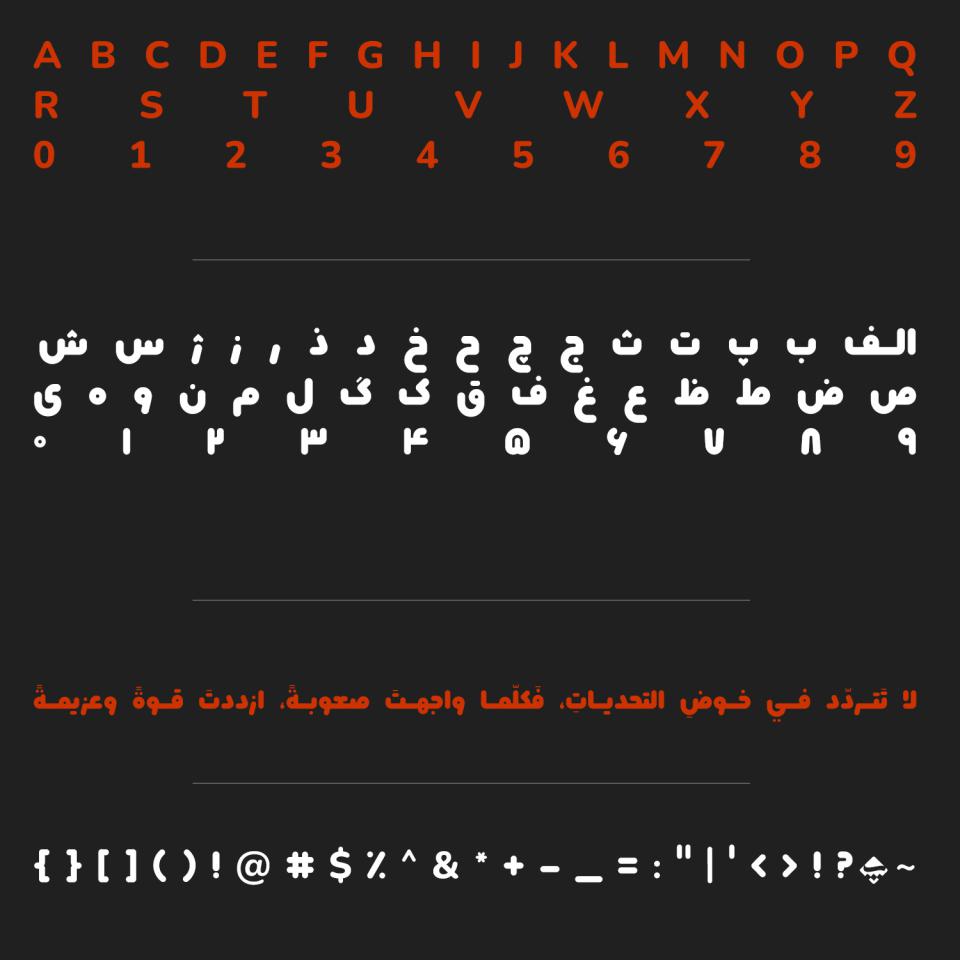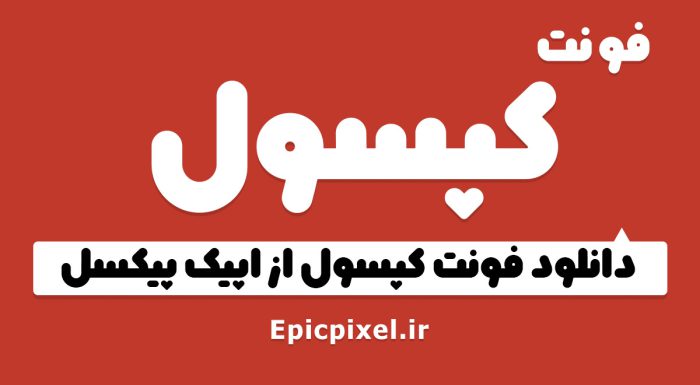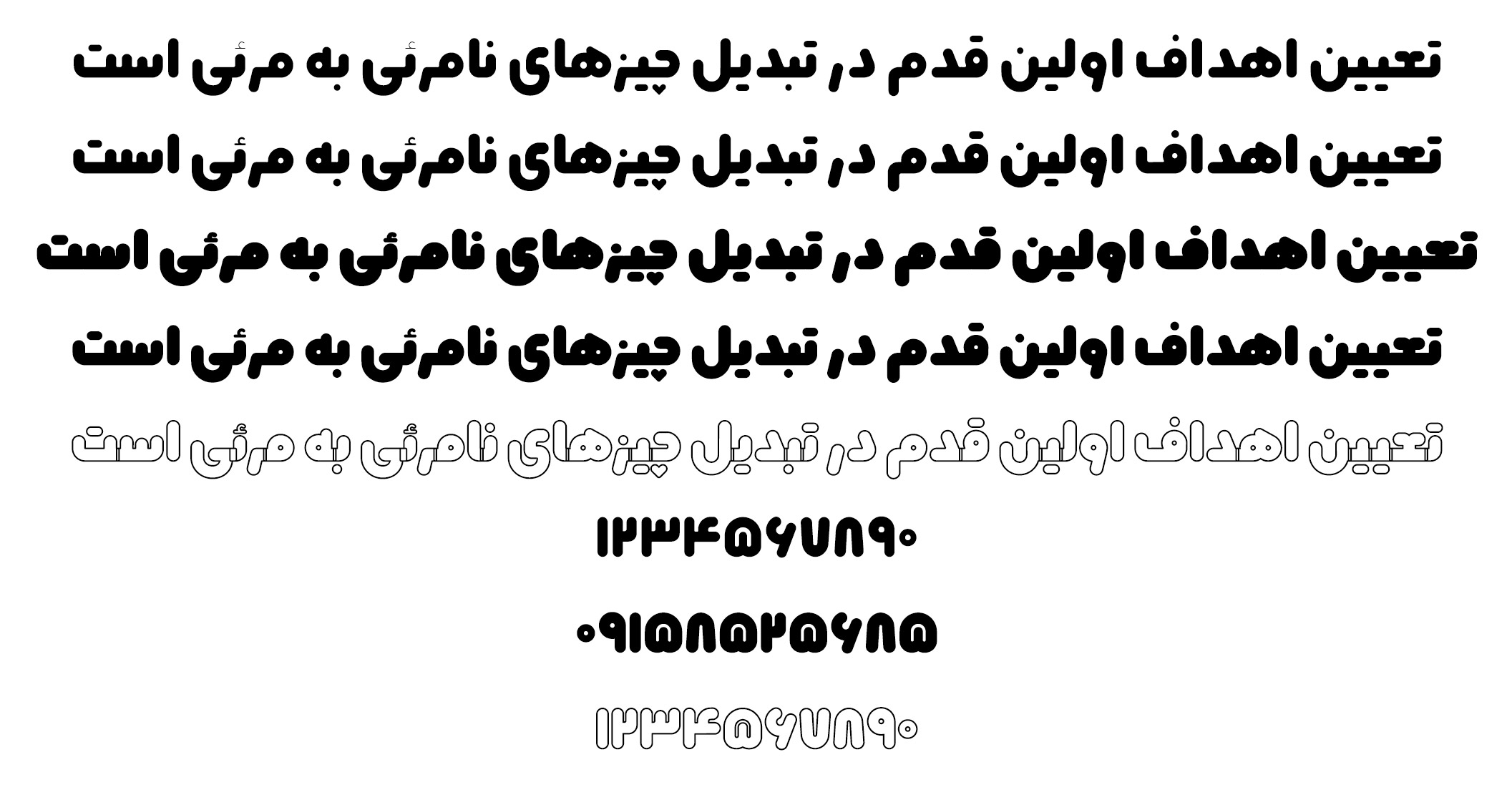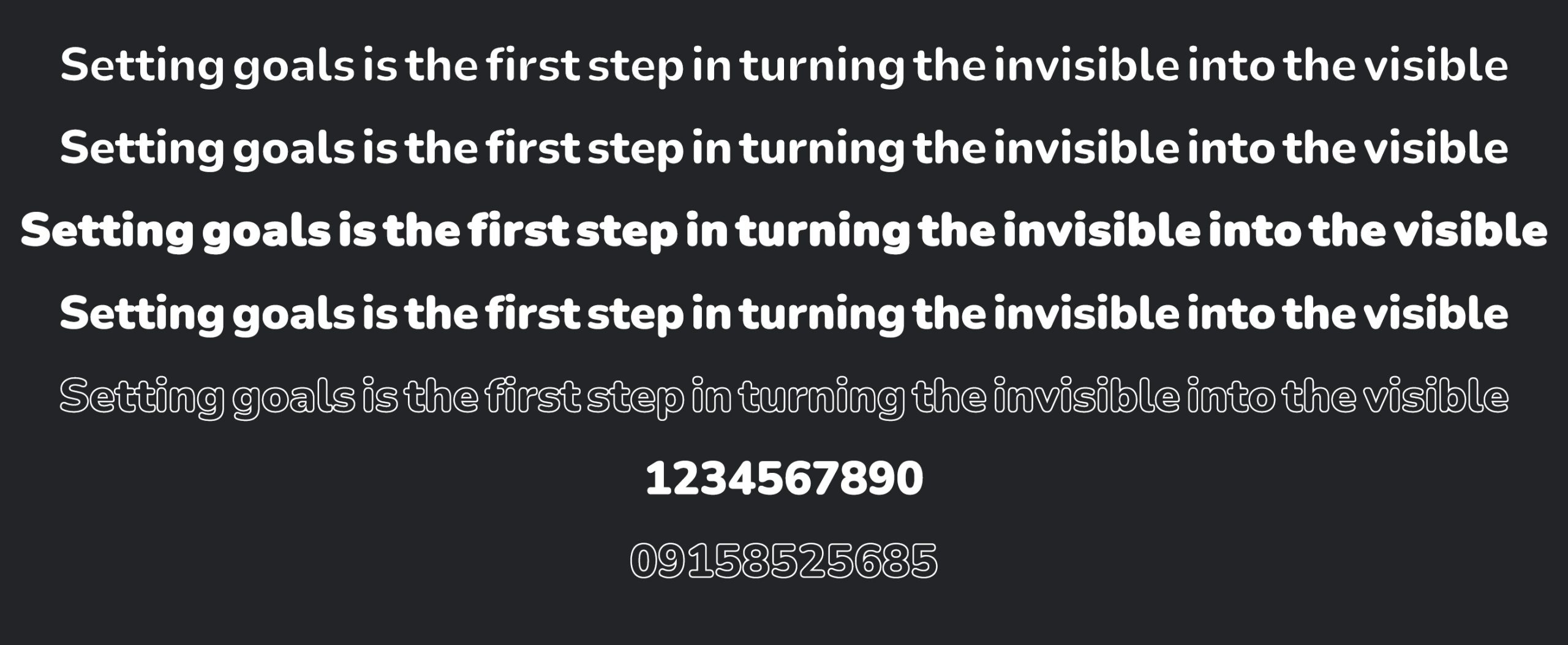
فونت کپسول، با طراحی مدرن و منحصربه فردش، روحی تازه به پروژه های گرافیکی شما می بخشد. این فونت، با ظاهری فانتزی و در عین حال خوانا، برای طراحی لوگو، عناوین جذاب، بسته بندی محصولات و تبلیغات، انتخابی ایده آل است. حروف کپسول، با فرم های گرد و نرم خود، حس صمیمیت و دوستانه ای را القا می کنند و به همین دلیل، برای پروژه های مرتبط با کودکان و نوجوانان نیز بسیار مناسب است.
یکی از ویژگی های برجسته فونت کپسول، تنوع در حروف جایگزین است که به شما امکان می دهد تا طراحی های خلاقانه تری داشته باشید. این فونت، با پشتیبانی کامل از زبان فارسی و اعراب، خیال شما را از بابت نمایش صحیح متون راحت می کند. همچنین، هماهنگی زیبای حروف فارسی و لاتین در این فونت، آن را برای استفاده در پروژه های چند زبانه نیز مناسب می سازد.
اگر به دنبال فونتی هستید که به طرح های شما جلوه ای خاص و متمایز ببخشد، فونت کپسول گزینه ای بی نظیر است. این فونت، با طراحی جذاب و ویژگی های کاربردی خود، به شما کمک می کند تا پیام خود را به بهترین شکل ممکن به مخاطب منتقل کنید.
| ⭐ توضیحات | مجموعه ای کامل از فونت های کپسول و نسخه شبیه سازی شده اپیک کپسول